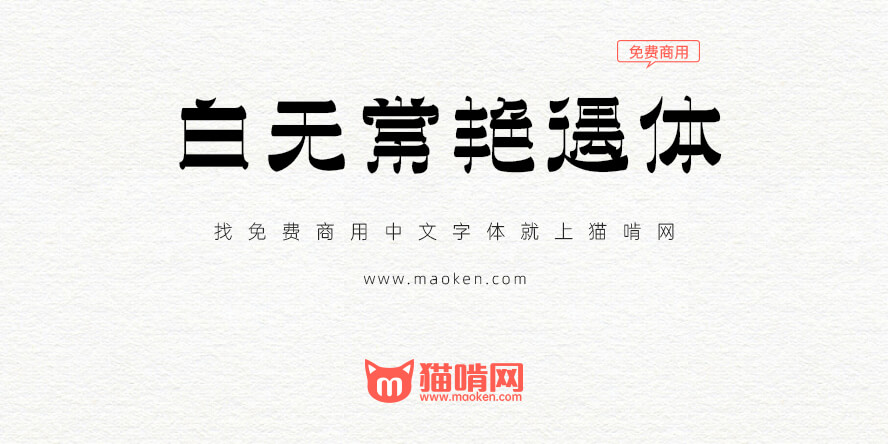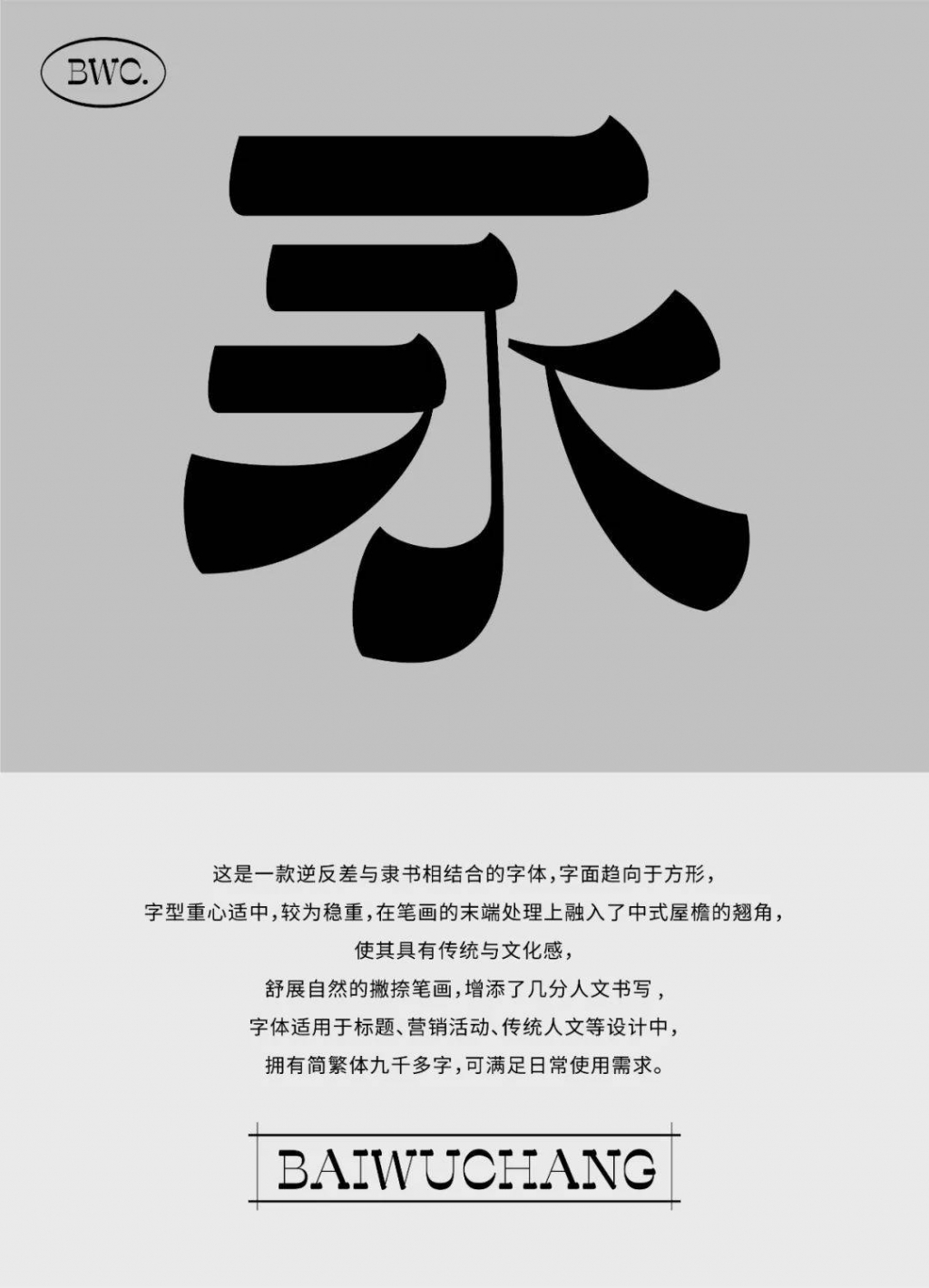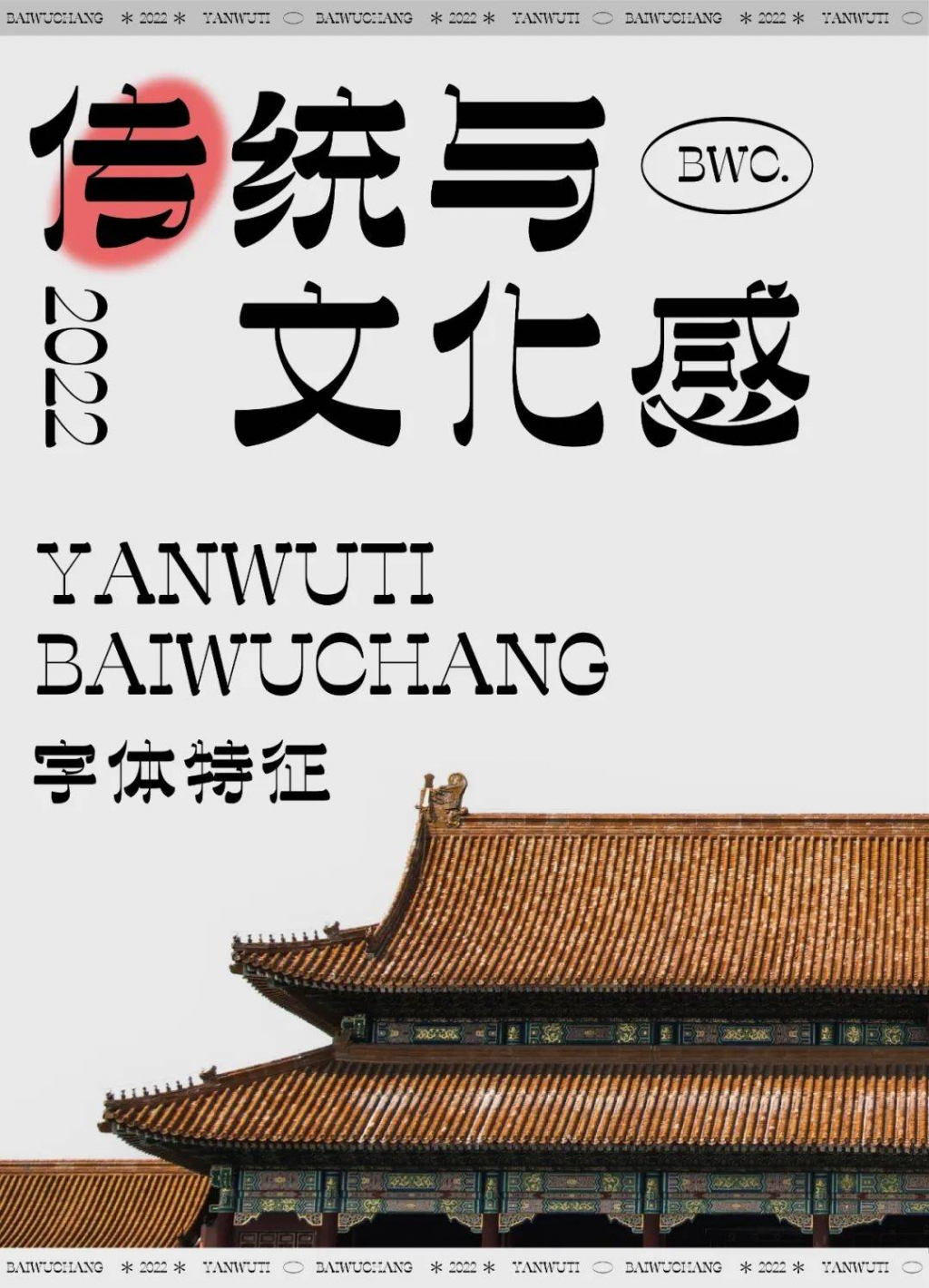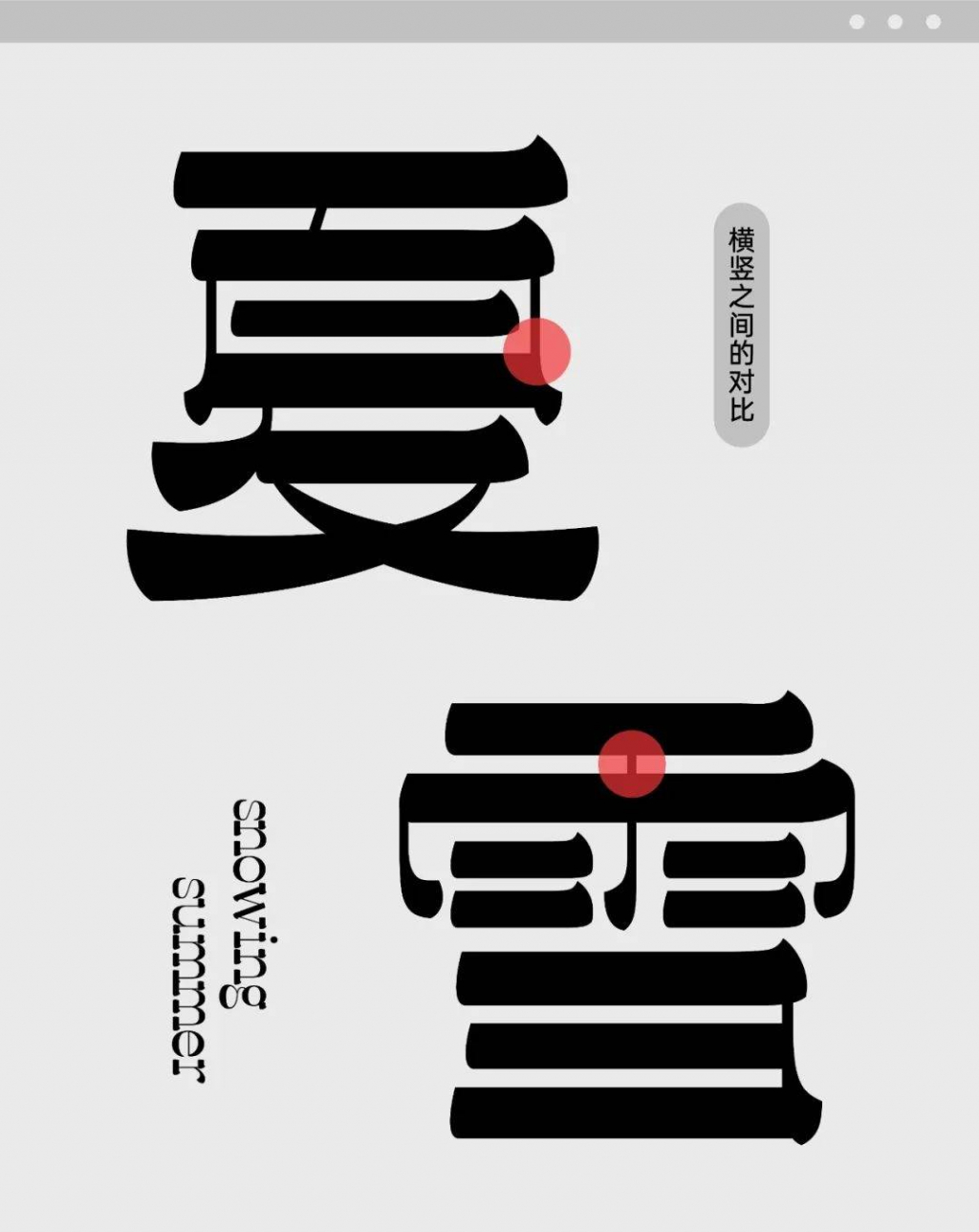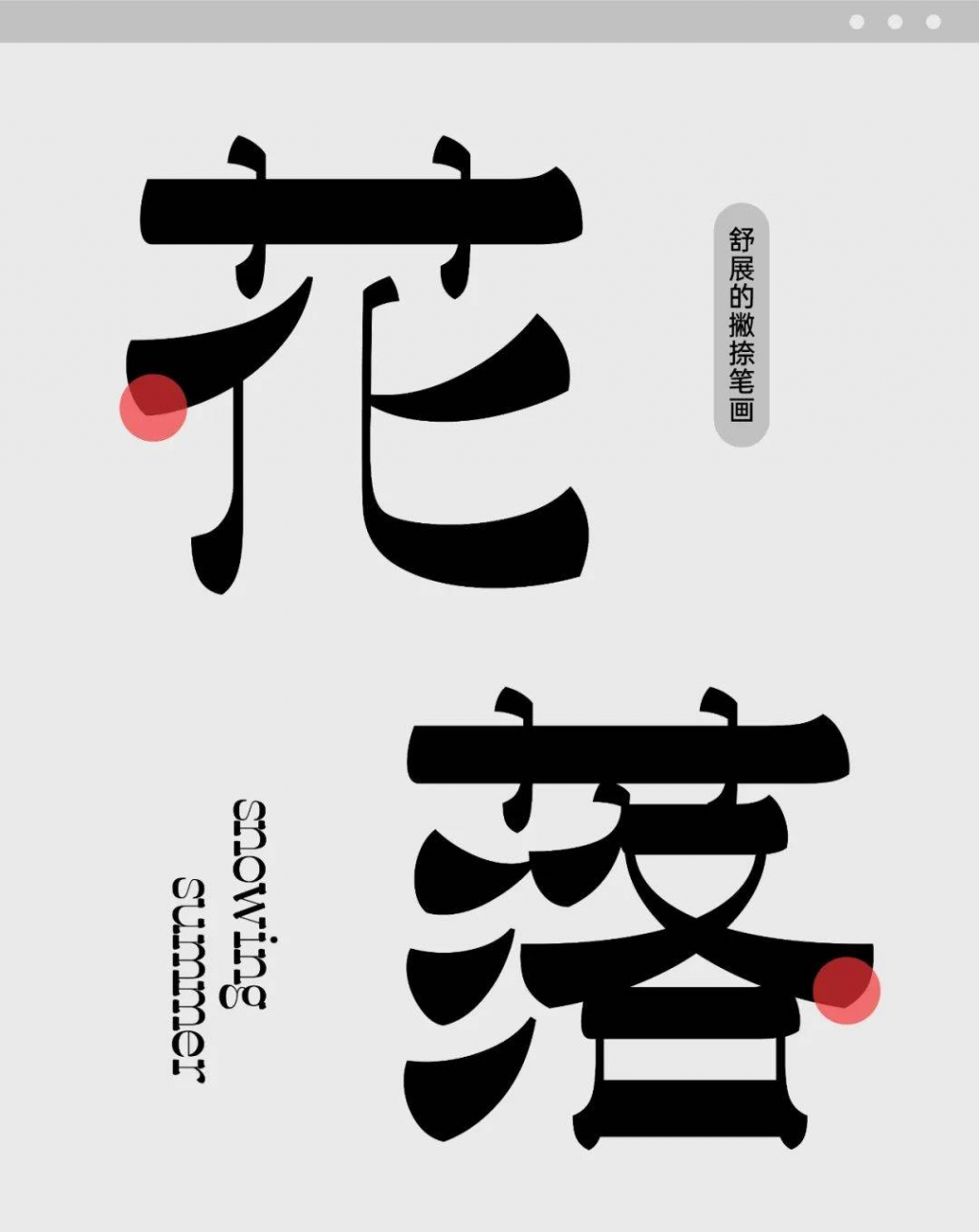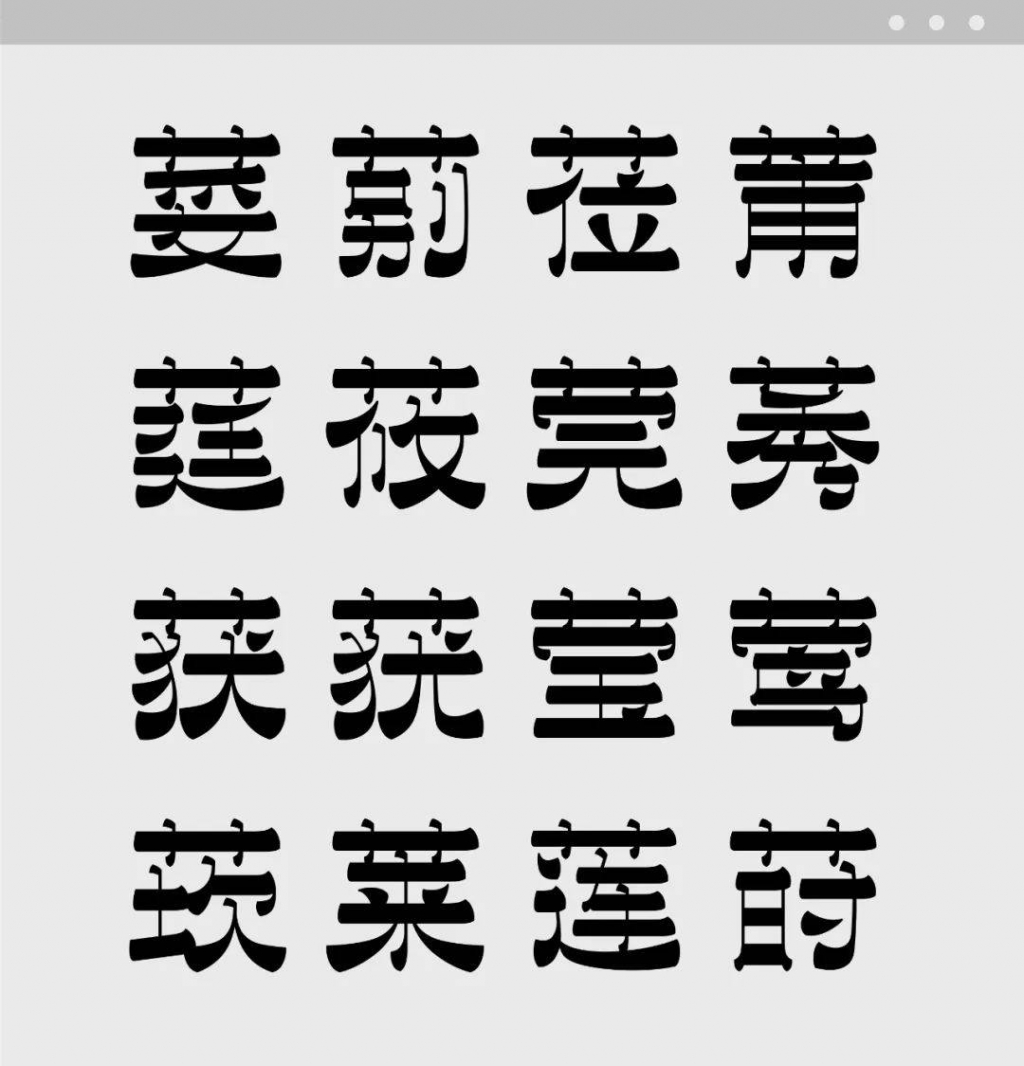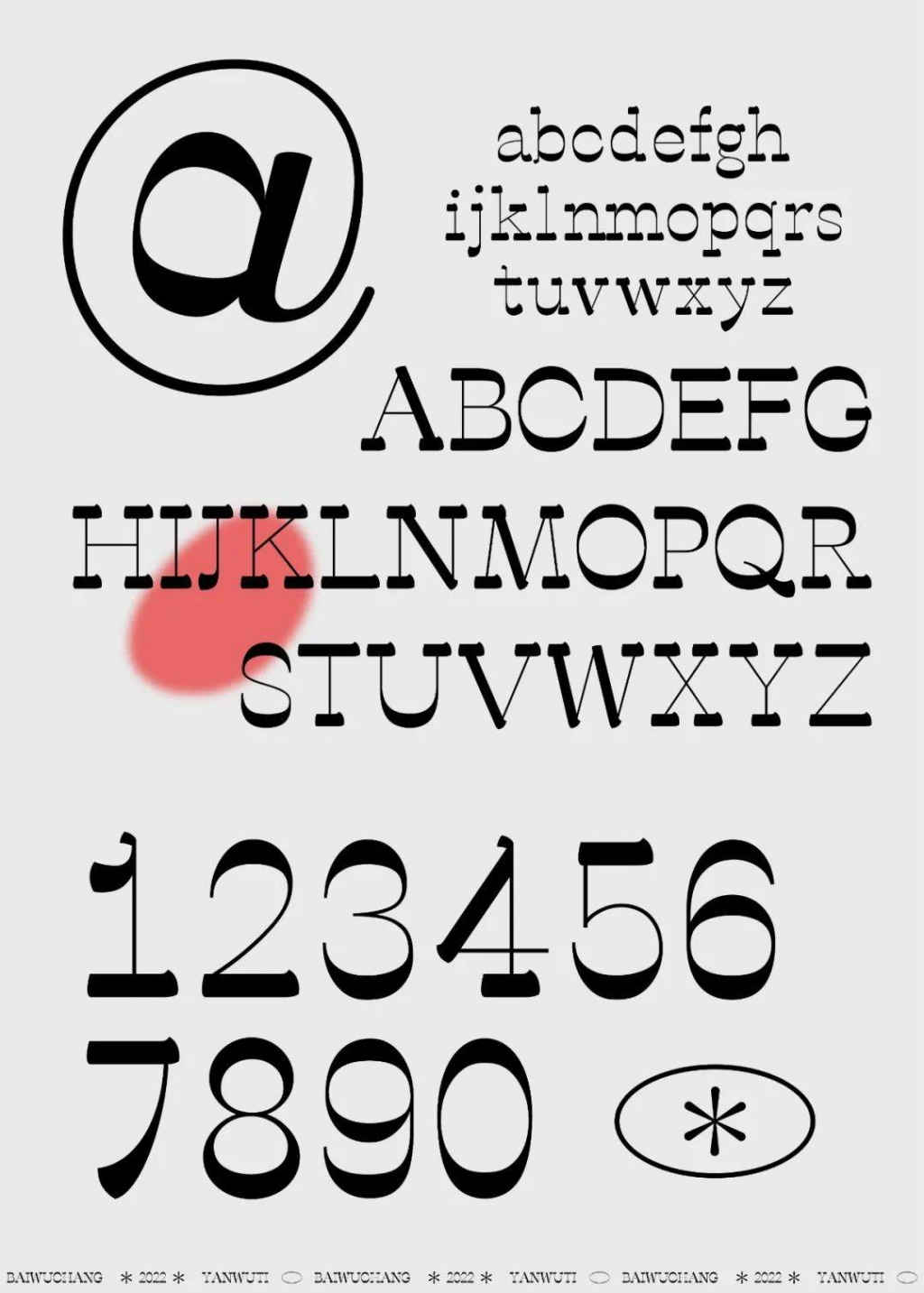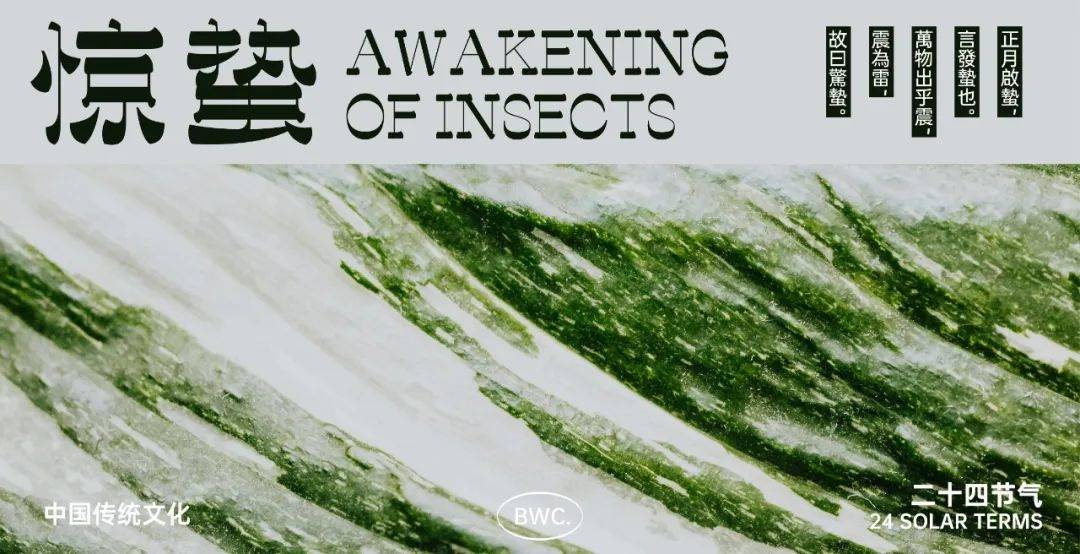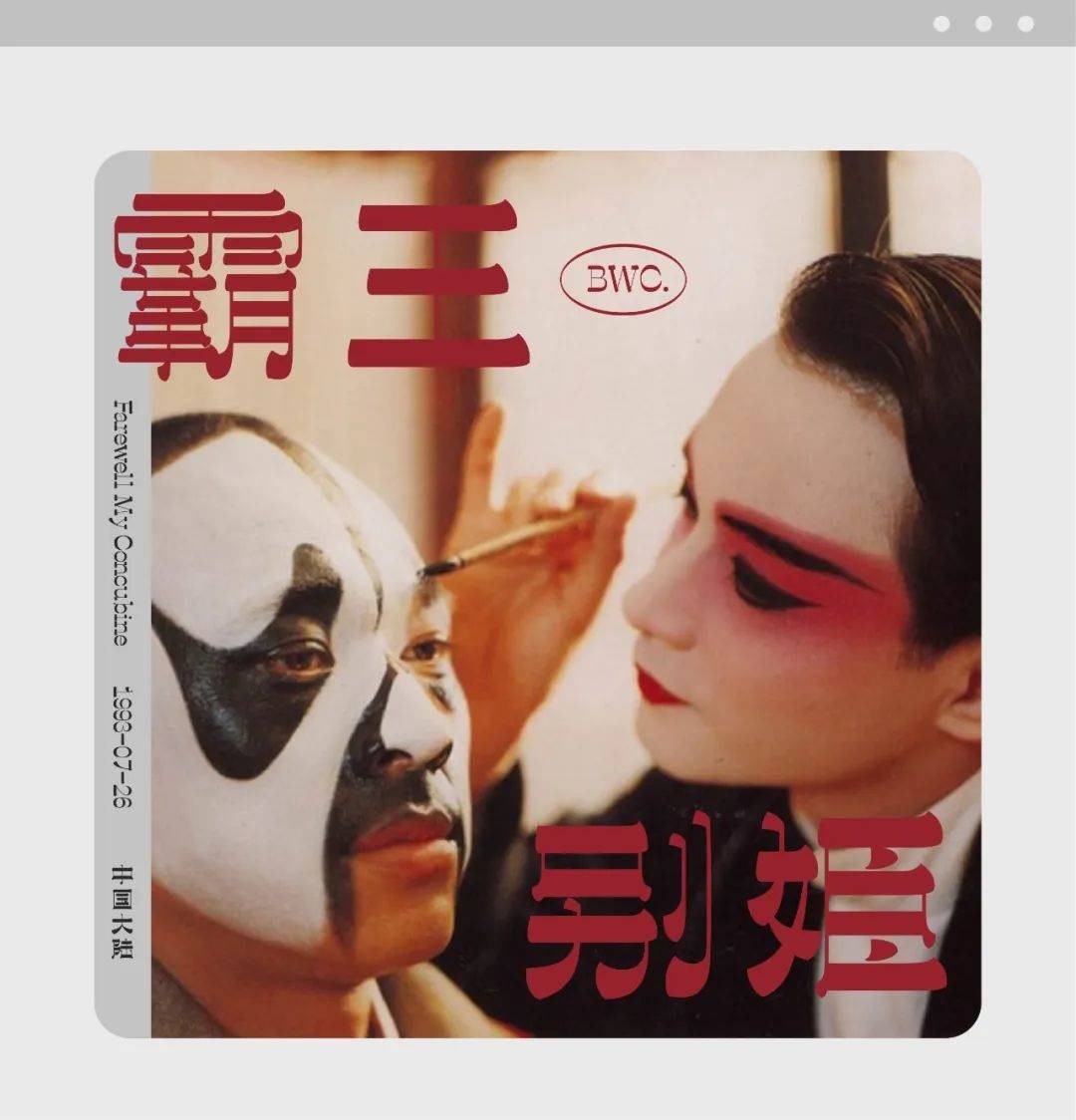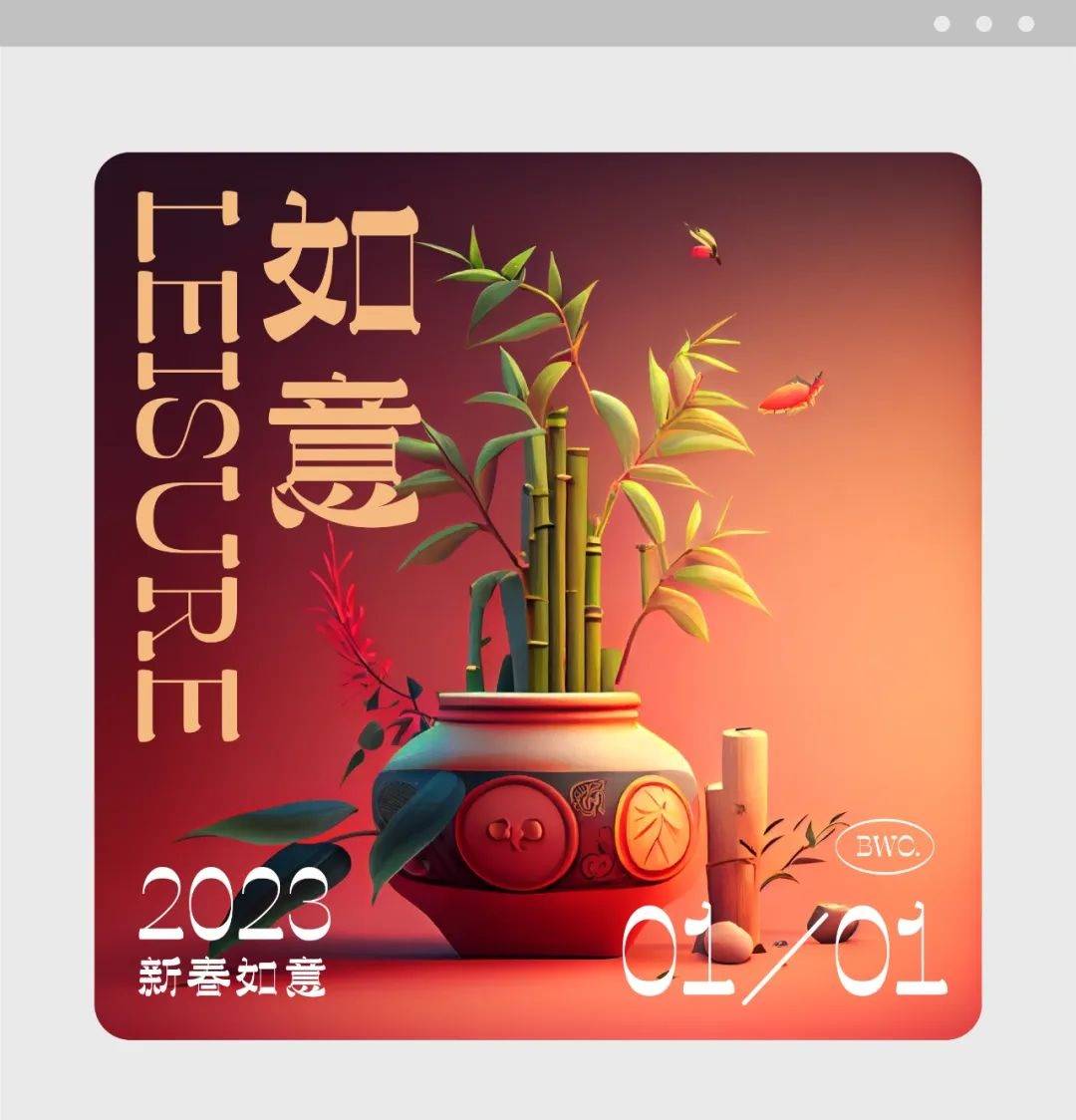
这是一款逆反差与隶书相结合的字体,字面趋向于方形,字型重心适中,较为稳重,在笔画的末端处理上融入了中式屋檐的翘角,使其具有传统与文化感;舒展自然的撇捺笔画,增添了几分人文书写的感觉,字体适用于标题、营销活动、传统人文等设计中。
艳遇体应用的整体效果也非常的出色,适合做标题字体~
这也太丑了 名字也取得很难听
4.另字型美丑与否,是个人主观审美,每个人标准不一样,而在实际使用中,更重要的是在应用场景是否合适;
对于用户来说,名字叫什么反而没那么重要,更关心能否在自己的作品或项目中合理应用。